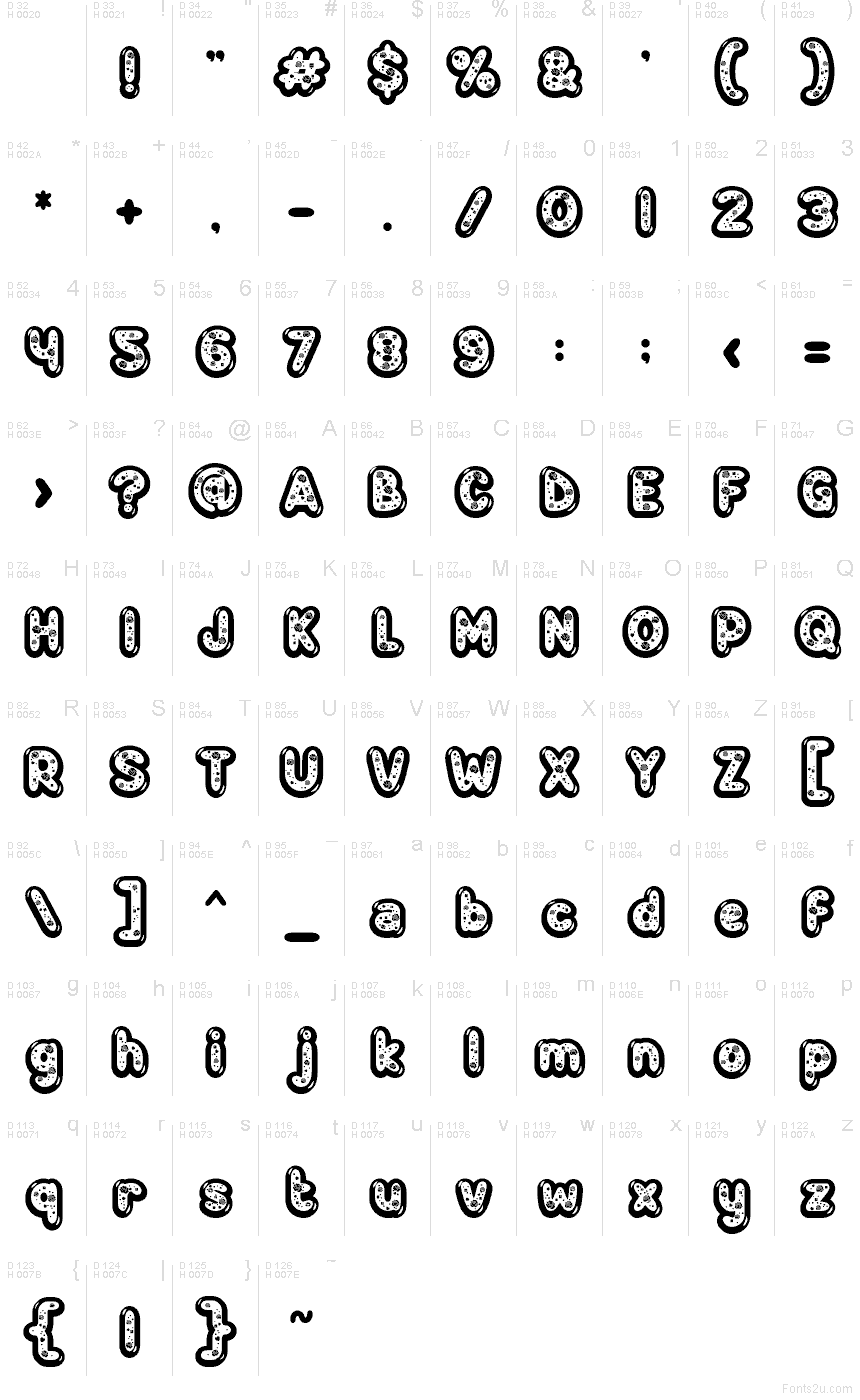
Cake Couture Eight
Cake Couture Eight von Putracetol Studio ist eine kostenlose Display-Schrift, die mit ihrem verspielten Backstuben-Charme überzeugt. Die Buchstaben wirken wie mit Zuckerguss verziert, sind dick schwarz umrandet und mit winzigen Streuseln, Punkten und kleinen Rosen verziert – das lässt das Alphabet handgefertigt und weniger wie ein gewöhnliches Design wirken.